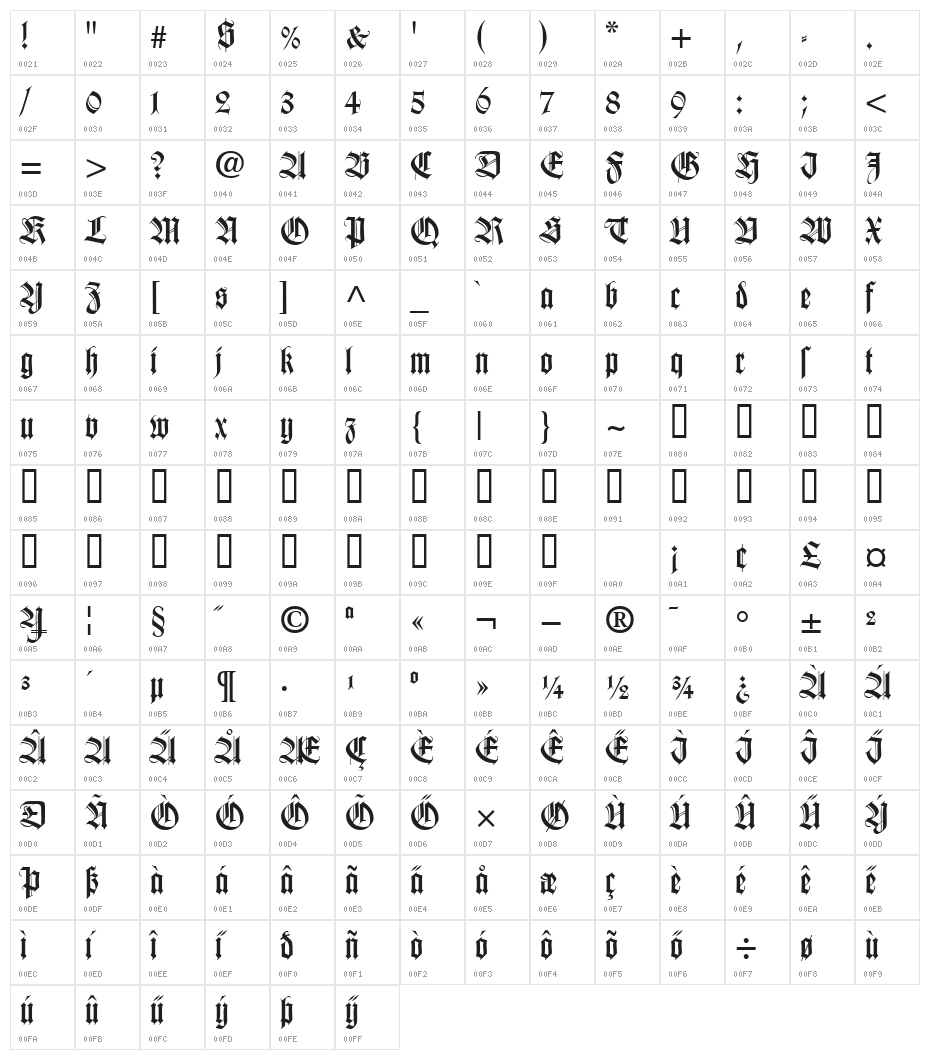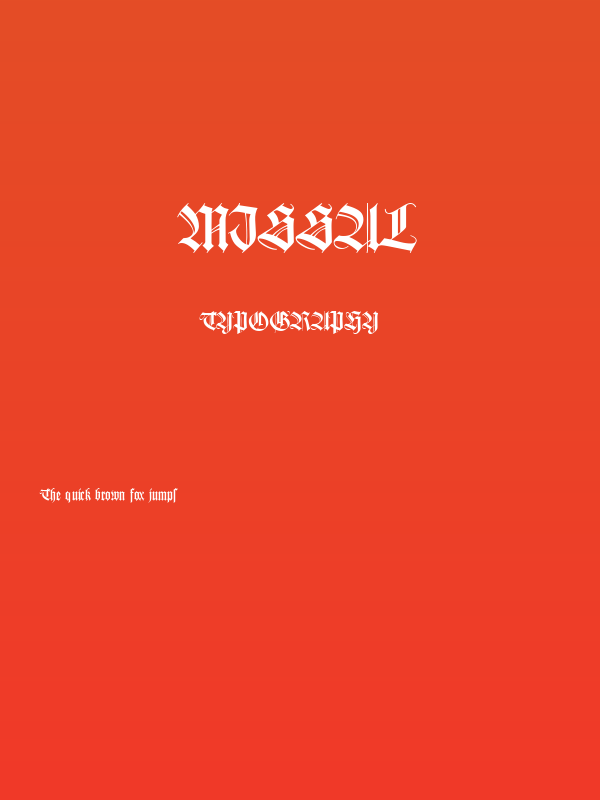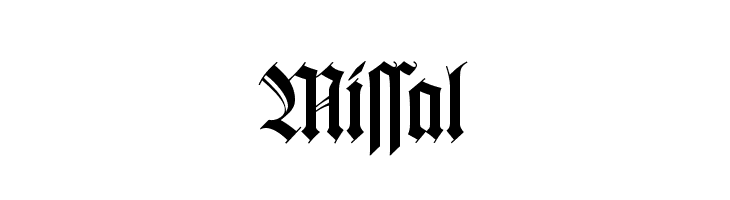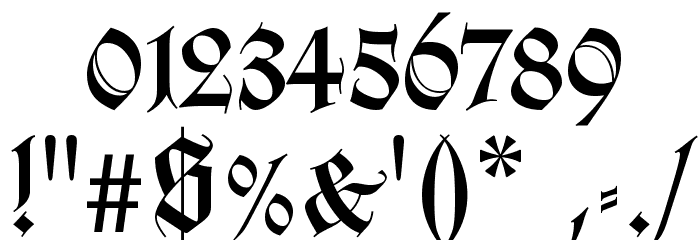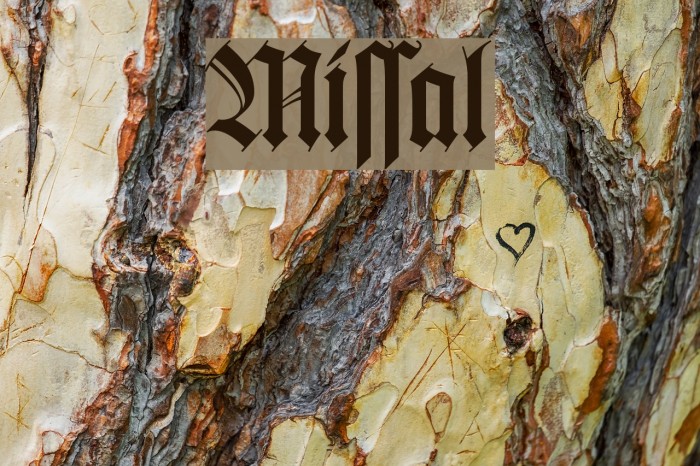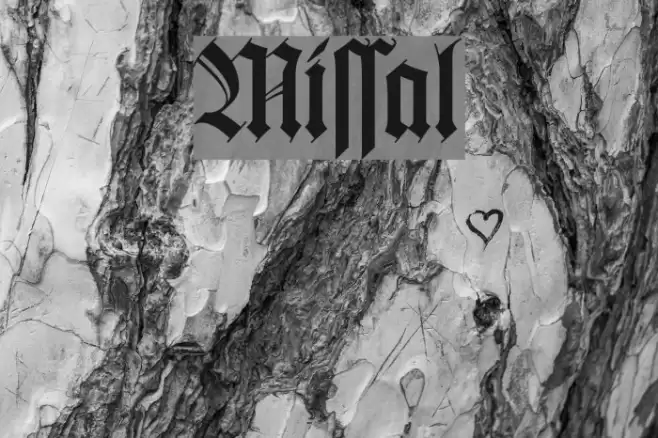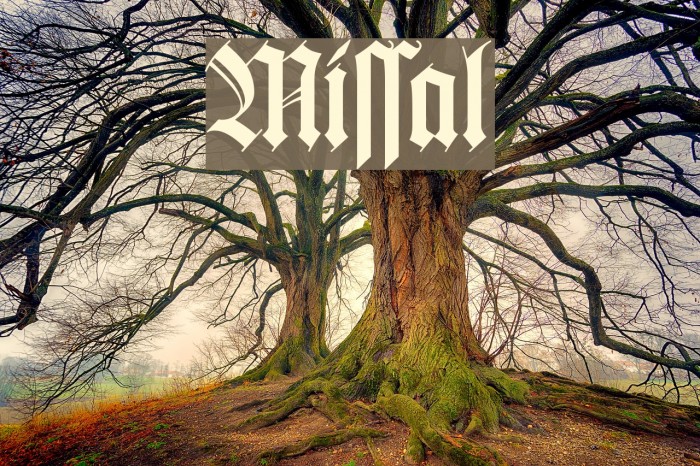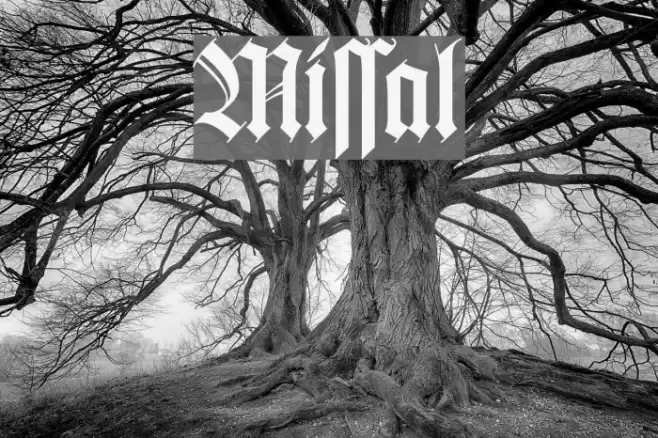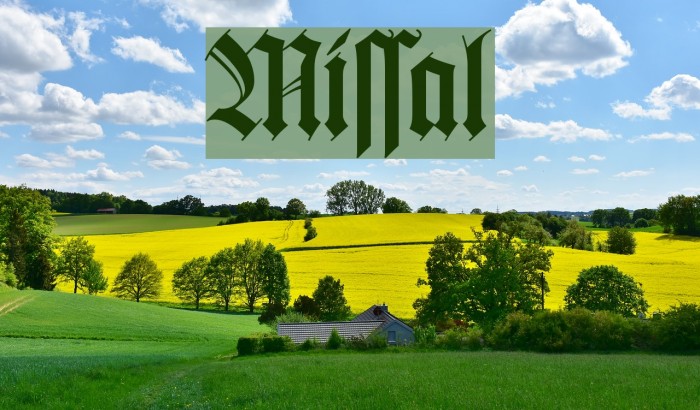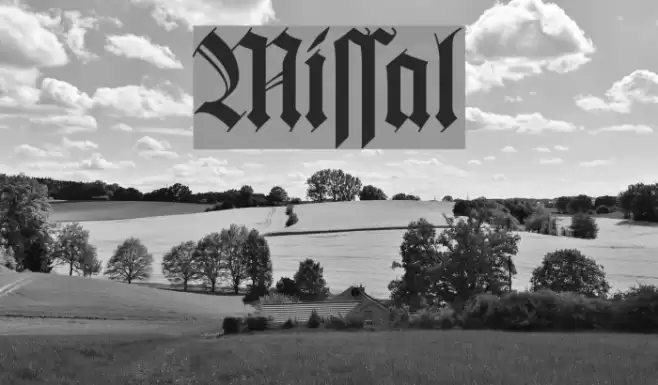
Missal Font
| Caz de utilizare | Headlines, Logos, Decorative text |
| Proiecte propuse | Ideal for certificates, wedding invitations, historical documents, and branding that requires a classic and formal touch. |